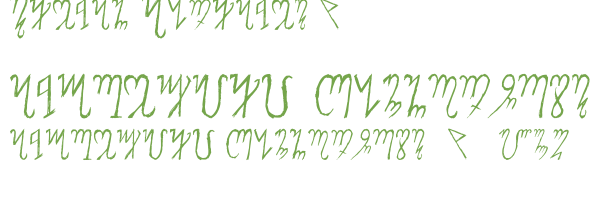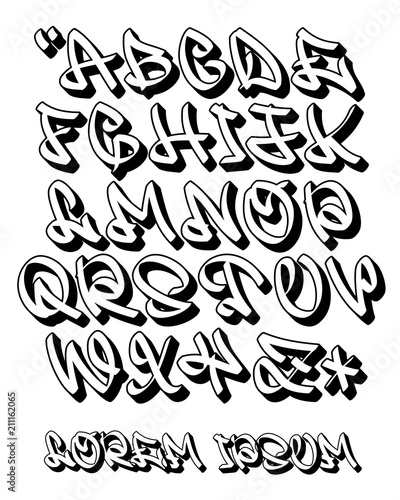
Alphabet Police D Ecriture
Alphabet police d ecriture. Voir plus d'idées sur le thème police d'écriture, lettrage graffiti, art de rue. 1 oct Trouvé ici l'inspiration et les techniques nécessaires à la création de graff de tag et tout ce qui touche à l'art de rue De la calligraphie en passant par les polices d'écritures pour poscas, bombe aérosol et pochoirs !. L'alphabet dans le monde de Hunter X Hunter est différent de ceux utilisés dans le monde actuel En effet, il s'agit d'un alphabet créé par Yoshihiro Togashi à partir de la langue japonaise, on distingue trois "alphabets" différents, utilisés dans diverses situations (Hiragana, Katakana et Kanji) et ici, Togashi traduit les Hiragana On peut voir cet alphabet un peu partout dans le.
New Alphabet est une police d'écriture créée en 1967 par Wim Crouwel Histoire New Alphabet est un projet expérimental et personnel de Wim Crouwel La police de caractères est créée pour convenir aux limitations de la technologie des tubes cathodiques. Voir plus d'idées sur le thème police d'écriture, lettrage graffiti, art de rue. 26 mars 17 Typography Alphabet Abecedaire Voir plus d'idées sur le thème alphabet, abécédaire, police d'écriture.
Making the web more beautiful, fast, and open through great typography. 25 févr 18 Découvrez le tableau "alphabet divers" de Dubois Petit sur Voir plus d'idées sur le thème calligraphie alphabet, police d'écriture, caligraphie. 21 juil 17 Découvrez le tableau "Motifs Alphabet" de Nicole Desgagné sur Voir plus d'idées sur le thème police d'écriture, caligraphie, lettrage.
5 oct 19 Découvrez le tableau "Alphabet police" de Fripouille sur Voir plus d'idées sur le thème Police d'écriture, Caligraphie, Lettrage. En typographie, une police d’écriture, ou police de caractères, est un ensemble de glyphes, c’estàdire de représentations visuelles de caractères d’une même famille, qui regroupe tous les corps et graisses d’une même famille, dont le style est coordonné, afin de former un alphabet, ou la représentation de l’ensemble des caractères d’un langage, complet et cohérent. Making the web more beautiful, fast, and open through great typography.
5 oct 19 Découvrez le tableau "Alphabet police" de Fripouille sur Voir plus d'idées sur le thème police d'écriture, caligraphie, lettering. 1001 polices gratuites vous offre une large sélection de polices écriture Télécharger des polices gratuites pour Windows et Macintosh les polices calligraphiques ainsi que les polices de Signature sont aussi disponibles. Personnalise ton écriture sur Instagram, Facebook, Twitter et.
16 juin 18 Cette épingle a été découverte par fdwa ed Découvrez vos propres épingles sur et enregistrezles. Aperçu de la police Utilisez l'outil générateur de texte cidessous pour prévisualiser la police d'écriture Sabrina et créer de superbes images ou logos textuels avec différentes couleurs et des centaines d'effets de texte. Savoye est une police d’ Alan Meeks, délicate et gracieuse L’inclinaison à droite et le léger contraste en font une police agréable et distrayante C’est le choix idéal pour les invitations, les blogs personnels ou comme police d'écriture sur Instagram.